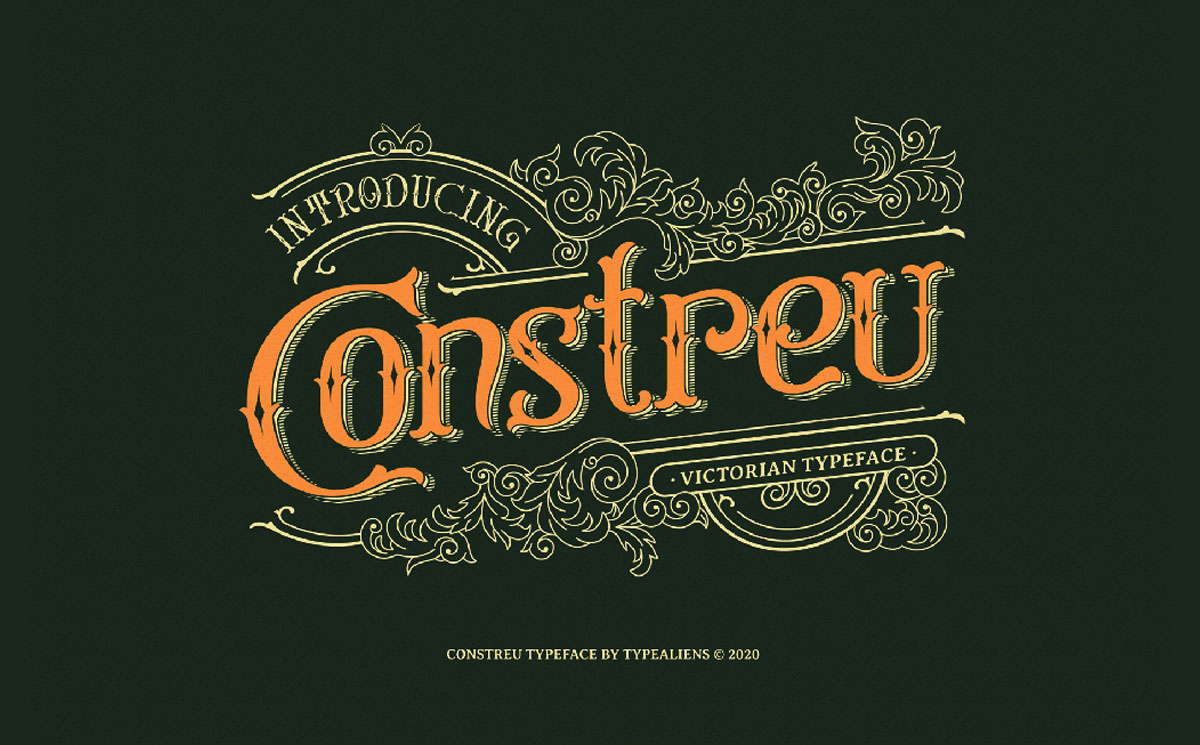
Trong thế giới thiết kế đồ họa đương đại, xu hướng hoài cổ (vintage & retro) luôn giữ một vị thế độc tôn nhờ khả năng truyền tải cảm xúc sâu lắng, sang trọng và đầy tính nghệ thuật. Font chữ cổ điển SVN Constreu Việt Hoá chính là một tác phẩm typography xuất sắc, kết hợp hoàn hảo giữa nét vương giả châu Âu thế kỷ trước và tính chuẩn xác của ngôn ngữ tiếng Việt. Đây sẽ là sự lựa chọn lý tưởng cho các nhà thiết kế đang tìm kiếm linh hồn cổ điển đích thực cho các ấn phẩm thương hiệu cao cấp.
Khám Phá Vẻ Đẹp Vượt Thời Gian Của Font Chữ Cổ Điển SVN Constreu Việt Hoá
Kiến trúc chữ viết luôn là tấm gương phản chiếu tinh thần thời đại. SVN Constreu được lấy cảm hứng từ các bản khắc kim loại và nghệ thuật in ấn thủ công phương Tây giai đoạn phục hưng, nơi mỗi đường nét đều chứa đựng sự tỉ mỉ, kiêu hãnh và trau chuốt. Khi được Việt hóa hoàn chỉnh bởi đội ngũ SVN, bộ phông chữ này không chỉ giải quyết triệt để rào cản dấu thanh trong tiếng Việt mà còn giữ trọn vẹn tỷ lệ vàng của các ký tự gốc, mở ra không gian sáng tạo vô tận cho cộng đồng sáng tạo tại Việt Nam.
1. Đường Nét Thiết Kế Đậm Chất Hoàng Gia và Tinh Tế
SVN Constreu gây ấn tượng thị giác mạnh mẽ ngay từ cái nhìn đầu tiên nhờ cấu trúc chân chữ (serif) sắc sảo, độ tương phản thanh – đậm (contrast) được căn chỉnh hài hòa tuyệt đối. Các đường cong elip mềm mại kết hợp cùng những nét thẳng dứt khoát tạo nên một nhịp điệu typography vừa uy nghiêm, quyền quý, lại vừa thanh thoát và trang nhã.
Từng đường nét của SVN Constreu mô phỏng chuẩn xác kỹ thuật khắc bản in cổ điển, mang lại cảm giác hoài niệm, sâu lắng nhưng không hề lỗi thời. Sự sắc nét này giúp các thiết kế tiêu đề, bìa sách hay bao bì sản phẩm cao cấp dễ dàng thu hút ánh nhìn và tạo dựng niềm tin về một thương hiệu có bề dày lịch sử và đẳng cấp vượt bậc.
2. Việt Hóa Chuẩn Xác Với Hệ Dấu Thanh Tự Nhiên
Một trong những thách thức lớn nhất khi sử dụng các font chữ cổ điển phương Tây cho tiếng Việt là hiện tượng dấu thanh bị lệch, thô hoặc phá vỡ cấu trúc cân đối của con chữ. SVN Constreu Việt Hóa đã khắc phục hoàn toàn nhược điểm này bằng việc thiết kế lại toàn bộ hệ thống dấu tiếng Việt (ngã, hỏi, sắc, huyền, nặng, mũ âu, ơ, ê, ô,…).
Các dấu thanh được tinh chỉnh riêng biệt để ăn khớp với từng con chữ cụ thể, đảm bảo khoảng cách dòng (leading) và khoảng cách chữ (kerning) luôn đồng nhất, không gây hiện tượng chồng chéo hay rối mắt khi trình bày các đoạn văn bản dài. Nhờ đó, tính thẩm mỹ và độ đọc (readability) của văn bản tiếng Việt được nâng lên mức tối đa.
3. Bộ Ký Tự Mở Rộng, Glyphs và Ligatures Phong Phú
Điểm sáng giá tạo nên đẳng cấp của font SVN Constreu chính là hệ thống ký tự thay thế (stylistic alternates) và ký tự nối đôi (ligatures) vô cùng đa dạng. Phông chữ cung cấp hàng loạt các biến thể chữ hoa cách điệu với những đường nét uốn lượn (swashes) đậm tính nghệ thuật cổ điển.
- Ký tự nối đặc biệt (Ligatures): Tự động kết hợp các cặp chữ thường gặp như fi, fl, st, ct tạo nên dòng chảy thị giác liền mạch, mô phỏng lối viết tay nghệ thuật.
- Chữ hoa trang trí (Swash Alternates): Tạo điểm nhấn đắt giá cho chữ cái đầu dòng (Drop Cap) hoặc các chữ cái mở đầu trong tên thương hiệu, giúp bố cục trở nên sinh động và độc bản.
- Hệ ký tự số và biểu tượng hoài cổ: Bao gồm các con số kiểu cổ điển (old-style figures) và hệ thống dấu câu đồng bộ, đáp ứng tiêu chuẩn khắt khe của các ấn phẩm in ấn chuyên nghiệp.
4. Khả Năng Ứng Dụng Đa Ngành Linh Hoạt
Không bị giới hạn trong một phong cách cụ thể, SVN Constreu Việt Hoá thể hiện sự linh hoạt tuyệt vời trên nhiều chất liệu và định dạng thiết kế khác nhau. Đây là công cụ đắc lực cho các dự án đòi hỏi sự sang trọng, chiều sâu và tính truyền thống:
- Nhận diện thương hiệu: Phù hợp cho logo, bộ nhận diện của các thương hiệu thời trang cao cấp, trang sức, đồng hồ, spa & resort, quán cà phê phong cách vintage hoặc quán bar speakeasy.
- Bao bì sản phẩm: Thiết kế nhãn chai rượu vang, hộp xì gà, bao bì trà thượng hạng, nến thơm thủ công hay mỹ phẩm hữu cơ mang phong cách hoàng gia.
- Ấn phẩm truyền thông & Xuất bản: Trình bày bìa tiểu thuyết lịch sử, tạp chí kiến trúc – nghệ thuật, poster phim tài liệu, thiệp cưới phong cách châu Âu quý phái.
- Giao diện số: Ứng dụng làm tiêu đề cho website khách sạn nghỉ dưỡng, landing page sản phẩm thủ công tinh xảo, đem lại trải nghiệm thị giác ấn tượng cho người dùng.